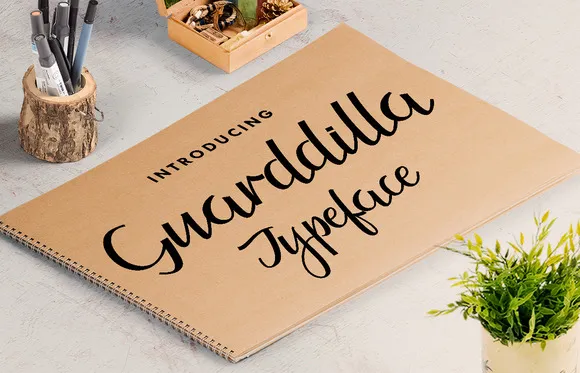
Guarddilla Typeface
Olá a todos! Estou aqui uma descrição envolvente para a Guarddilla Typeface, uma nova fonte caligrápica introduzida por Apon Bahrainy. Esta elegante e criativa fonte é perfeitamente adaptada para diversos projetos de design gráfico, como o título da sua próxima peça visual, logotipos, cartas pessoais ou profissionais, convites de casamento, etiquetas de embalagens, newsletters, materiais publicitários, adesivos e até mesmo camisas personalizadas. Guarddilla Typeface oferece uma experiência única em estilo caligráfico que é ideal para quem busca um toque especial e autêntico em suas criações. Ela foi concebida para adaptar-se à variedade de necessidades do design, seja para decorar um cartão de convite ou incorporar no design de um site profissional. A fonte é gratuita para uso pessoal. Para utilizar esta fonte comercialmente, basta seguir o link fornecido e adquirir uma licença. Se você está procurando por uma font caligráfica que se destaca em seu projeto, não há melhor opção do que a Guarddilla Typeface. Experimente-a e veja como ela pode transformar sua designação!
Designer: Apon Bahrainy